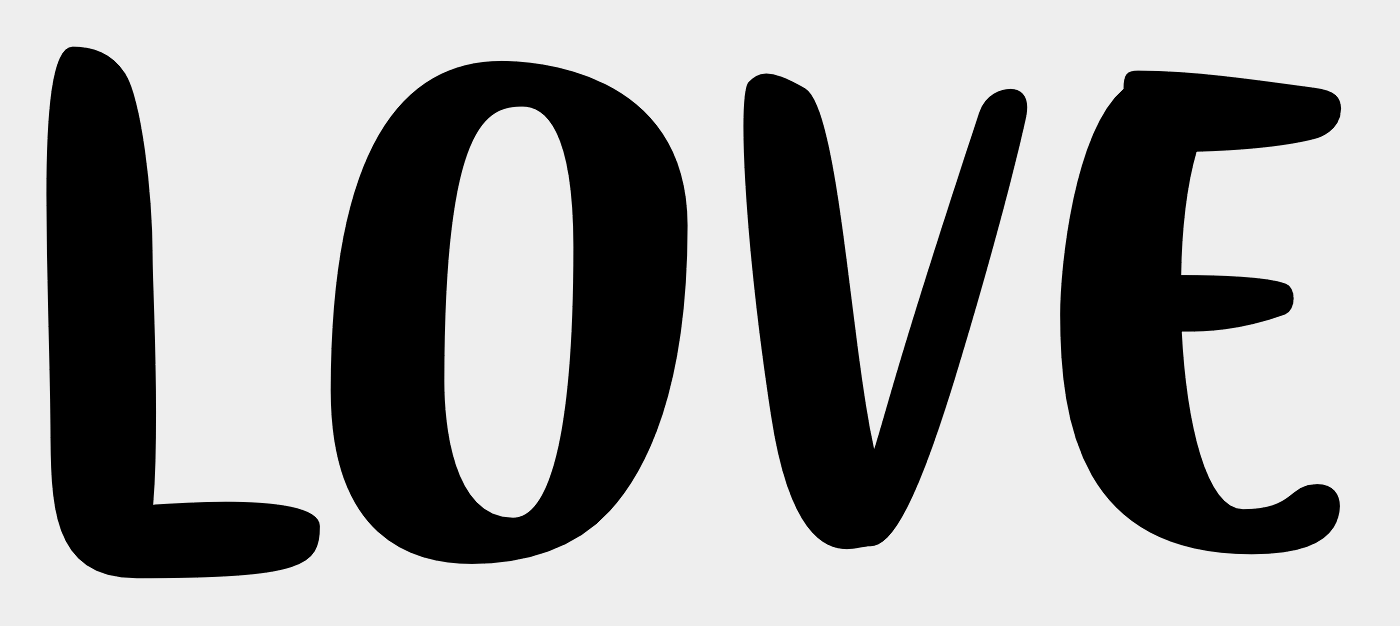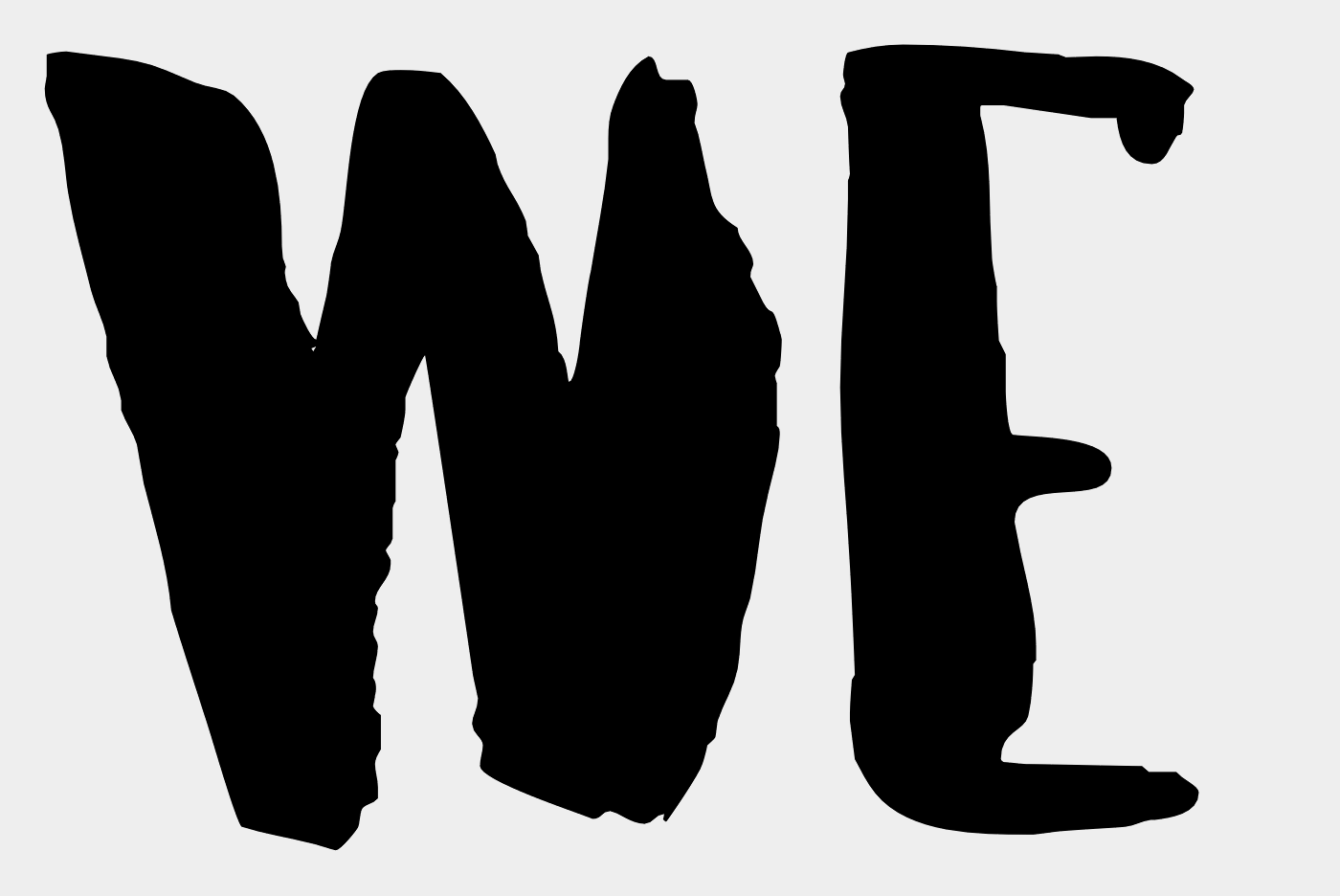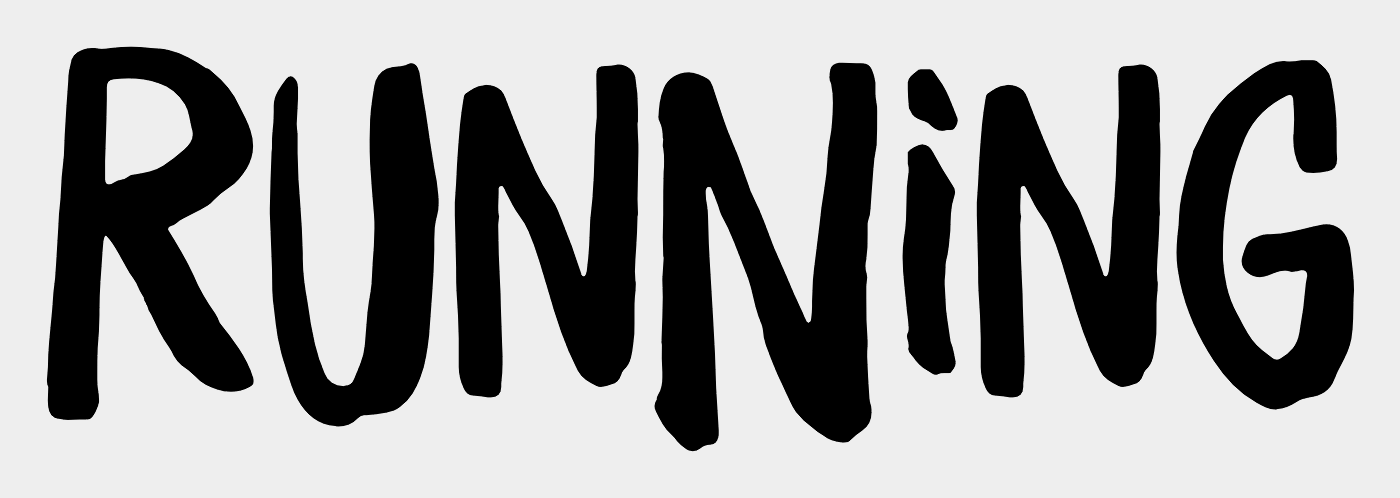
Welche Schrift bzw. was passt dazu?
3 verschiedene N, 2 verschidene I. Also selbstredend keine Schrift im Sinne von Font.
Daher hier am passendsten: 1 Rundpinsel, 1 Tuschefäßchen.
Viele Fonts wie z.B. die folgenden haben einen ähnlichen Pinsel-Duktus (und OT-Alternativen und damit einen Tuschefässchen-
Effekt). Bestimmt kennt der eine ander hier noch einen ähnlichen Freefont.
Würde das I gern bei Bedarf in ein We love running abändern.
Das ist aber rundum scheußlich. Also alles. Und damit meine ich gar nicht mal das Herz mit dem Läufer an sich. Meinst du nicht, dass du das besser hinbekommst, wenn du das komplett neu machst, ohne auf irgend etwas Vorgefertigtes zurückzugreifen?
Ich fände ein Herz, das zwar stilisiert ist, aber einem echten  Herz ähnelt, gut. Oder irgend einen anderen Gegenstand, der Liebe ausdrückt. Könnte man zur Vedeutlichung ja rot einfärben. Wo stammt eigentlich die typische Form des stilisierte Herzens her? Weiß das jemand? Ich glaub, ich werd mich noch eher an das große Eszett gewöhnen als an die klassische Arschbacken-Herzform.
Meine beiden Cent:
– Das Herz zentriert unter der Sonne fand ich stimmiger (evtl. Hintergrund verschieben)
– Den rechten Portrait-Block würde ich weiter nach rechts rutschen
– Den chinesisch anmutenden Font finde ich inhaltlich etwas seltsam gewählt
Die senkrecht in die Höhe strebenden Baumstämme würde ich nicht mit Laufen in Verbindung bringen, weil die Bewegungsrichtung ja eine ganz andere ist. Aber zu den Bäumen passt für mich die Schrift im unteren Beispiel eindeutig besser. Sie wirkt ruhiger, gerader, ausgeglichener, stabiler.
Edit: Mit der leicht chinesischen Anmutung hat bertel natürlich trotzdem Recht.
Mich irritiert der Versalsatz. Und im zweiten Bild wirkt die erste Zeile mit dem Herz dezentriert. Warum schreibst du den Text nicht selbst? Vielleicht mit einem dicken Edding? Eventuell einem mit flacher Spitze? Oder du schneidest dir die Spitze zurecht. Edding-Spitzen sind im Neuzustand so hart, dass ich mir auch vorstellen könnte, sie in Form zu schleifen. Vielleicht auf einer Dremel-Trennscheibe. Jedenfalls würde ich es eher mit einem Edding als mit einem Pinsel versuchen. Und mit einem Rundpinsel schon gar nicht.
Die Idee mit den frei schwebenden Fotos im Wald finde ich ganz gut. Auch die asymmetrische Anordnung der Fotos.
Habe die beiden Sachen korrigiert. Die Bäume als Motiv fand ich einfach sehr schön mit der Sonne und dann geht es ja jeden Samstag in den Wald. Idee ansonsten, die Bilder der Läufer (inzwischen sind wir über 50 :-) ) immer mal ergänzen oder austauschen und so ist halt noch Platz. Man könnte die aber auch etwas größer machen, bin mir nicht sicher.
Warum schreibst du den Text nicht selbst?
Soll nicht der ganz große Aufwand werden. Ich nutze jeden Woche für die Einladung andere Banner und ändere die dann immer mal ab bzw. ergänze einige Sachen. Jetzt halt gerade mal die Idee mit den Bildern einiger Läufer ...  Darf immer nicht viel Aufwand sein (ist es so schon genug), darf nichts kosten :-) und soll trotzdem gut aussehen und vor allem beachtet werden. Also alles im Rahmen und hobbymäßig. Wir sind jetzt seit über einem Jahr dabei und der Aufwand lohnt sich. Die Gruppe wird immer größer, immer bunter (Einheimische, Flüchtlinge, Studenten ... - Kinder, Frauen, Männer) und wir bekommen auch immer mehr Aufmerksamkeit.
Meine Gedanken:
• Baumhintergrund gefällt mir gut
• Der etwas gröbere Pinselschrift-Stil passt besser dazu
• Warum ist das Herz jetzt glossy?
• Würde mir eine schmalere Schrift zu dem »Baumraster« wünschen
• Schrift finde ich auch zu »chinesisch«
• Mal eine Variante mit WE in Herzgröße testen?
• Zeichenabstand finde ich zu eng
• Ist das Ursprungsmotiv von Dir? (Nachmachen und so …)
Das »We love running« mit Herz und Läufer könntest du aber als wiederkehrendes Motiv nutzen. Da würde sich etwas Aufwand schon lohnen.
Und der Versalsatz geht meiner Meinung nach wirklich gar nicht.
• Ist das Ursprungsmotiv von Dir?
• Wenn nicht: Du bekommst keine Probleme das einfach nach zu machen?
Habe ein kostenpflichtiges Abo bei Freepik und darf die Sachen damit verändern.
Warum ist das Herz jetzt glossy?
ändere ich wieder...
Würde mir eine schmalere Schrift zu dem »Baumraster« wünschen
Hast Du eine Empfehlung (Freefont)
Die sunrise gefällt mir schon mal wesentlich besser als die Varinate davor - Danke!
Freut mich! :-) Ob die aber jetzt schon das Non-Plus-Ultra ist, weiß ich nicht (kannst ja auch selber noch etwas bei Dafonts stöbern). Läuft auf alle Fälle noch zu eng, muss also noch etwas gesperrt werden. Das WE finde ich auch noch zu klein.
Und probier mal einen N-Wechsel:
Bonus: Wäre natürlich cool, wenn das Herz auch so angefressen wäre wie die Schrift. ;-)